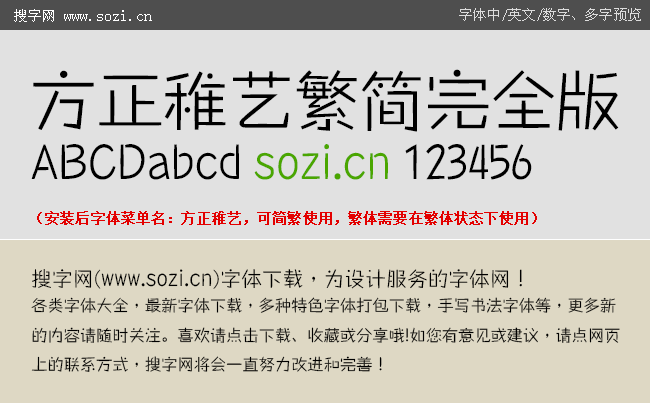
方正稚藝繁簡完全版(FZZhiYi)
搜字網(wǎng)提供一款可愛卡通風(fēng)格的方正稚藝繁簡完全版字體,這款字體非常漂亮,帶有卡通風(fēng)味,活潑而不死板,是你pc必裝的字體之一?梢詰(yīng)用于廣告設(shè)計(jì)、平面設(shè)計(jì)、印刷包裝、報(bào)紙雜志等行業(yè)。